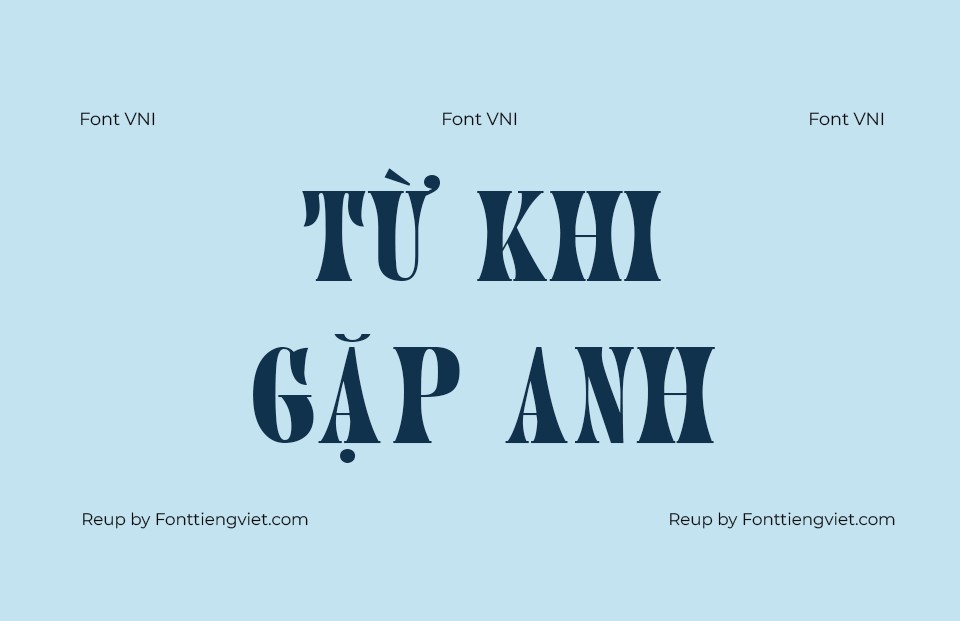
Font Việt hoá VNI Juni
Giới thiệu về Font Việt hoá VNI Juni trong thiết kế
Trong thế giới đồ họa, việc lựa chọn một Font Miễn Phí chất lượng luôn là ưu tiên hàng đầu của các nhà sáng tạo. Font Việt hoá VNI Juni nổi lên như một giải pháp hoàn hảo cho những ai đang tìm kiếm sự kết hợp giữa nét cổ điển và tính ứng dụng cao. Đây là bộ phông chữ được tinh chỉnh kỹ lưỡng, hỗ trợ đầy đủ bảng mã VNI giúp người dùng dễ dàng gõ tiếng Việt mà không lo lỗi hiển thị. Với đường nét thanh mảnh nhưng chắc chắn, bộ chữ này mang lại cảm giác chuyên nghiệp cho mọi bản thảo.
Đặc điểm nổi bật của Font Việt hoá VNI Juni
Thiết kế tối ưu cho học đường
Font Việt hoá VNI Juni sở hữu cấu trúc chữ rõ ràng, dễ đọc, cực kỳ phù hợp cho các em học sinh và giáo viên khi soạn thảo giáo án hoặc làm bài thuyết trình. Sự tinh tế trong từng nét chữ giúp nội dung trở nên lôi cuốn, giảm bớt sự khô khan của các văn bản thuần túy.
Khả năng tương thích linh hoạt
Điểm mạnh của bộ font này là khả năng vận hành mượt mà trên nhiều phần mềm thiết kế từ cơ bản đến chuyên nghiệp. Dù bạn đang sử dụng Word, PowerPoint hay Photoshop, font chữ này vẫn giữ được độ sắc nét tuyệt đối, giúp các bảng tin nhà trường hay báo tường trở nên sinh động hơn bao giờ hết.